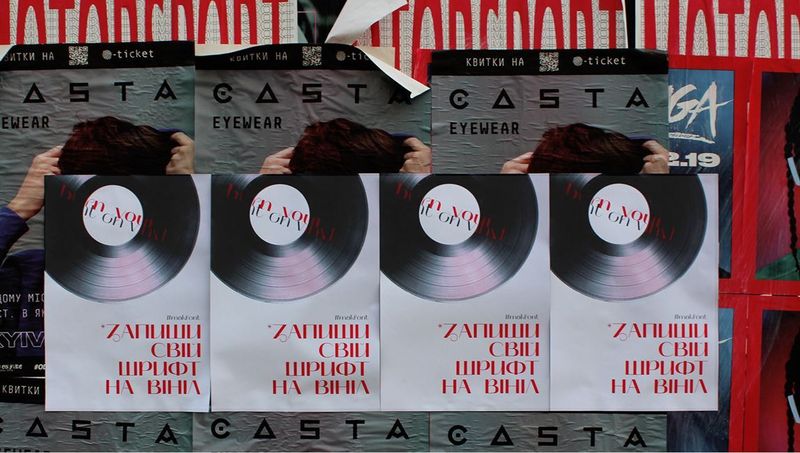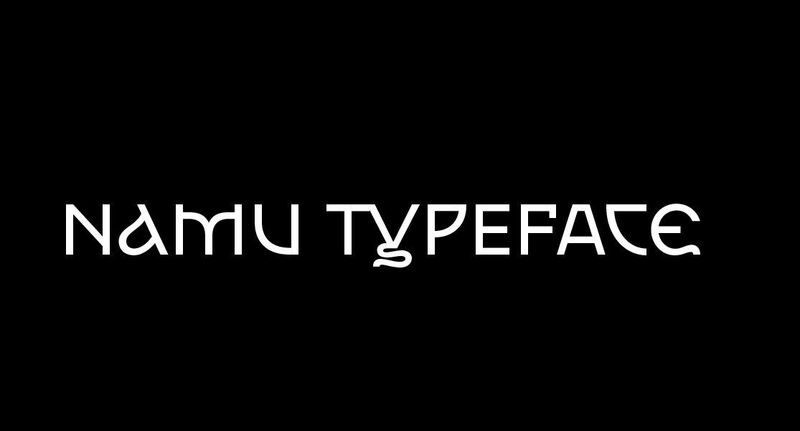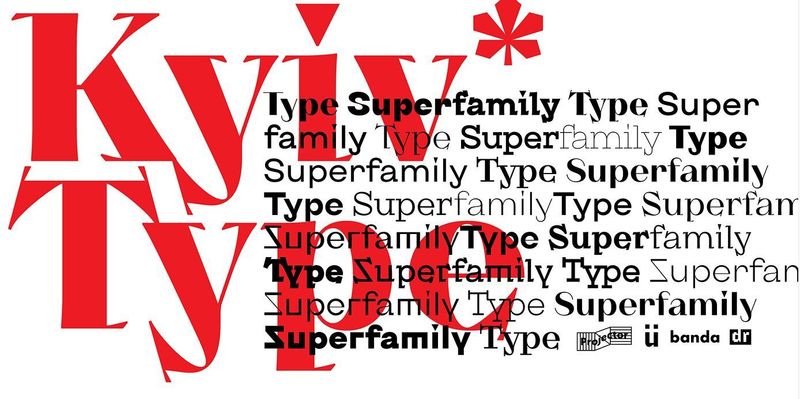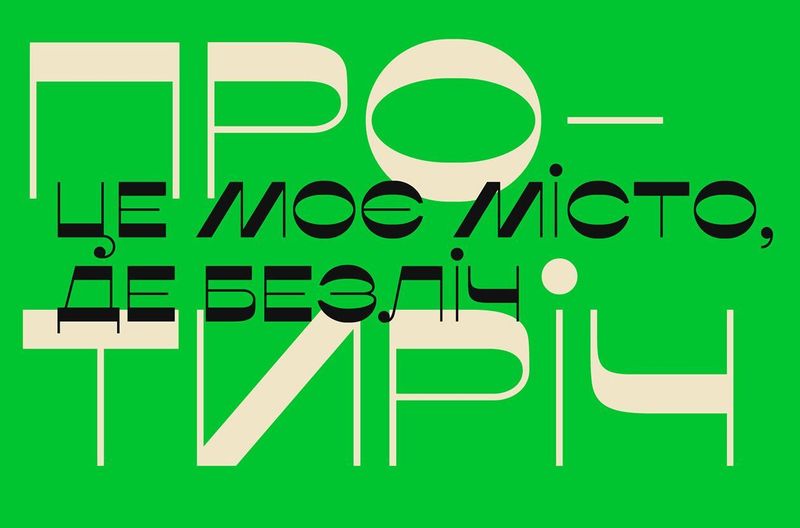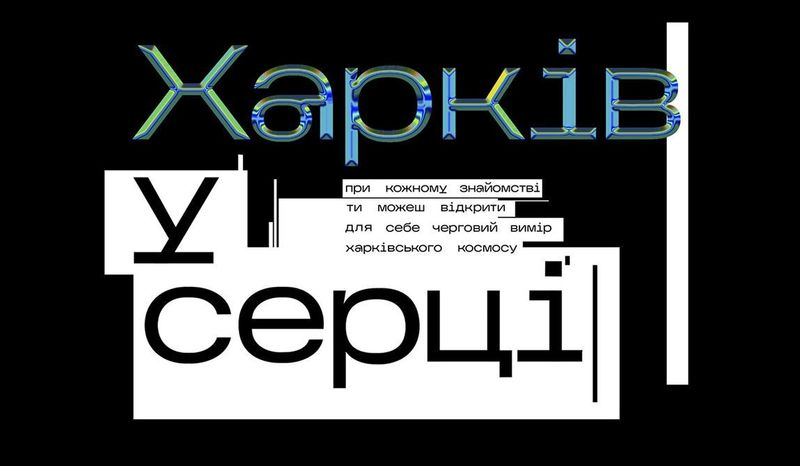
Безкоштовні шрифти з підтримкою української мови #2
В цій добірці представлені шрифти розроблені українськими дизайнерами.
1. Kyiv Type Це сучасний шрифт, що читається, створений Валерією Калашниковою. Він має безліч накреслень, включаючи Regular, Bold, Italic та Bold Italic. Шрифт підтримує українську мову та містить діакритичні знаки. В основу дизайну було покладено риси архітектури та меморіальних знаків міста Києва.
1. Misto Font Це дизайнерський шрифт, розроблений українським дизайнером та графіком Олексієм Ільєнком. Шрифт було створено у 2019 році спеціально для використання у міському середовищі, для показу назв вулиць, місць та інших об'єктів. "Misto Font" має простий та лаконічний дизайн, що дозволяє використовувати його на різних поверхнях та матеріалах. Він також містить підтримку української мови, зокрема кирилиці.
1. Kharkiv Tone це дизайнерський шрифт, розроблений українським дизайнером Ivan Datskov. Шрифт створювався спеціально для міста Харкова, і на його створення надихнули яскраві кольори та контрасти міської архітектури. Шрифт має унікальний дизайн, що добре підходить для використання у великих заголовках, плакатах та інших елементах дизайну. Він включає 2 зображення - Bold і Regular - і містить підтримку української мови, в тому числі кирилиці.
1. NAMU typefaces Wе сімейство шрифтів, які поєднують у собі елементи каліграфії та сучасного дизайну. Вони мають унікальний дизайн і доступні для використання у різних проектах та дизайнерських завданнях. Підходить для створення логотипів, банерів, візиток, упакування, рекламних матеріалів та інших графічних проектів.
1. MAK Варіативна версія популярного українського шрифту Мак. Це дисплейний шрифт з українським настроєм, натхненний українською музикою.Експерименти з історичними формами, контрастами, сміливими формами допомогли створити на її основі новий образ української кирилиці та латиниці. Гарнітура включає 4 безкоштовні стилі шрифту: Mak Regular Low, Mak Semibold High, Mak Extrabold, Mak Black High. Вони доступні за ліцензією Open Font License (OFL). Гарнітуру розробив Валентин Ткаченко у 2019-2022 роках.